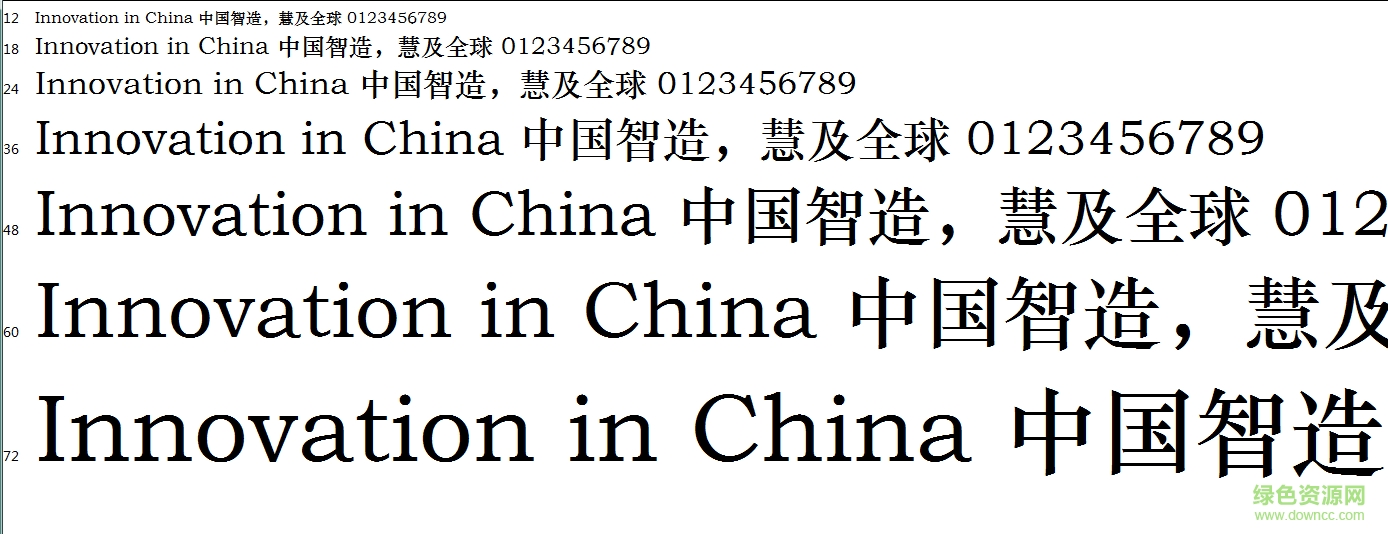
軟件介紹 軟件標(biāo)簽: 字體 增值稅發(fā)票字體是一款簡潔美觀的字體,此款字體廣泛應(yīng)用于增值發(fā)票單中,外形端正,粗細(xì)均勻,可直接導(dǎo)入至ps使用,操作非常簡單,喜歡的朋友歡迎來綠色資源網(wǎng)下載!字體安裝方法方法一:控制面板/字體/文件/安裝新字體;方法二:直接將字體復(fù)制到C:\WINDOWS\Fonts。方法三:針對win7系統(tǒng),用戶只需選中字體右鍵安裝即可。注意事項本站所有字體資源僅供個人學(xué)習(xí)與參考,如需商業(yè)使用請到相關(guān)官網(wǎng)授權(quán)。 軟件截圖 上一張下一張(1 / 1) 安裝詳細(xì)截圖 猜你喜歡 增值稅軟件 增值稅軟件 增值稅專用發(fā)票開票軟件是專門為用戶打造的增值稅計算工具,軟件可以幫助用戶打印出需要的增值稅發(fā)票,小編在這里整理了增值稅計算器、增值稅發(fā)票查詢平臺、百航增值稅開票打印工具、增值稅防偽稅控輔助,歡迎有需要的朋友到這里來體驗嘗試! 查看更多>> 增值稅電子發(fā)票閱讀器ofd 41.70M/中文/10.0/v3.20.830 官方綠色版下載 51增值稅電子普通發(fā)票軟件 18.59M/中文/2.5/v3.0.0000.9610 官方版下載 增值稅一般納稅人資格登記表 11KB/中文/5.5/doc版下載 阿拉丁增值稅計算器 42KB/中文/10.0/下載 增值稅小規(guī)模納稅人申報表 61KB/中文/8.3/最新版下載 2019增值稅一般納稅人申報表 40KB/中文/5.3/全套最新版下載 其他版本下載 標(biāo)題 大小 更新日期 下載 下載地址 電腦版 增值稅發(fā)票字體 點擊報錯 軟件無法下載或下載后無法使用,請點擊報錯,謝謝! 關(guān)閉報錯反饋 請描述您所遇到的錯誤,我們將盡快予以修正,謝謝! *必填項,請輸入內(nèi)容 本類最新 dreamweaver字體庫 首爾南山體字體 v1.06 官方版 潮字社風(fēng)云簡ttf 潮字社凌渡鯤鵬簡體字體 潮字社曾玉波手書簡字體 微博慧心字體 相關(guān)文章 Windows 7系統(tǒng)默認(rèn)字體還原技巧 Photoshop字體安裝使用方法和技巧 綠色資源網(wǎng)教你谷歌瀏覽器怎么調(diào)節(jié)字體大小 Mac下如何安裝字體?蘋果Mac系統(tǒng)安裝字體的三種方法 photoshop 缺少字體對照表(中英對照表)_字體中英文對照表大全 CDR字體列表缺少字體的解決方法 用戶評論 熱門評論 最新評論 發(fā)表評論 查看所有評論(0) 昵稱: 請不要評論無意義或臟話,我們所有評論會有人工審核. 字?jǐn)?shù): 0/500 (您的評論需要經(jīng)過審核才能顯示)